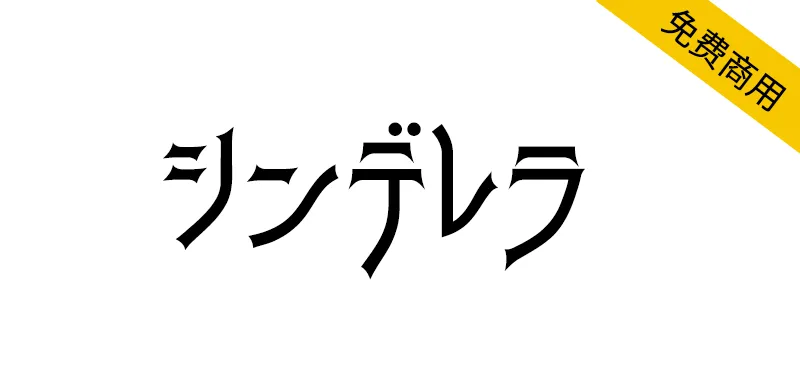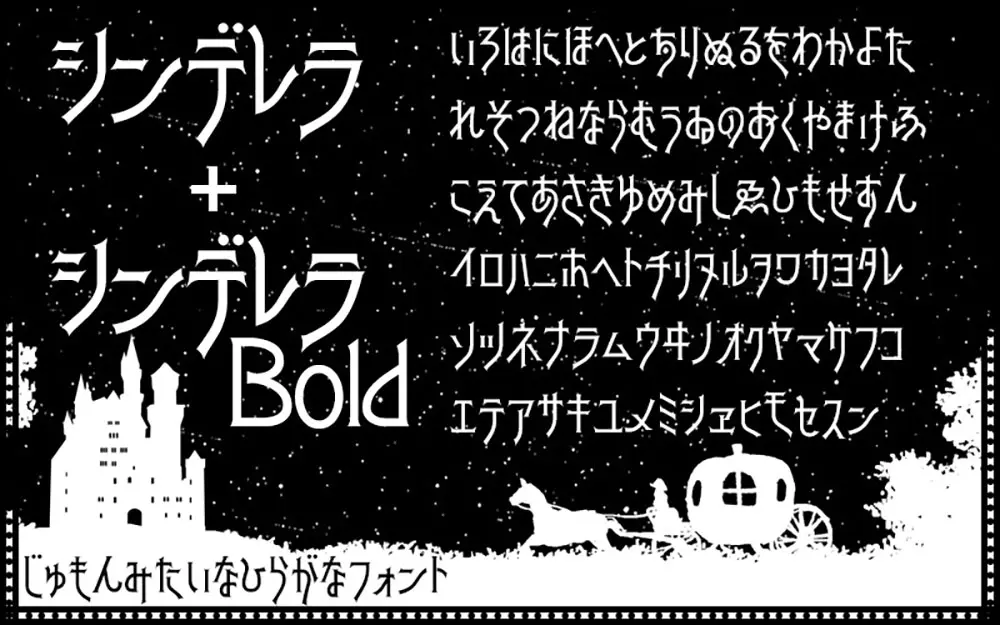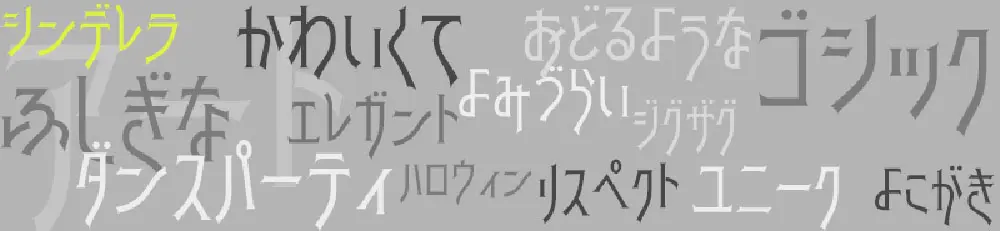
シンデレラ是從《Art Gothic》這一活版字體中得到靈感,以跳舞般的可愛和優雅為目標的字體。《Art Gothic》是1884年由Gustav Schroeder設計的,現在作為數字字體,各種供應商和設計師發佈了復刻版和修訂版。
『Art Gothic』という活版書體から著想を得て、 踴るようなかわいさと優雅さを目指したかなフォントです。『Art Gothic』は1884年にGustav Schroederによってデザインされたもので、現在ではデジタルフォントとして、様々なベンダやデザイナーが復刻版や改訂版をリリースしています。